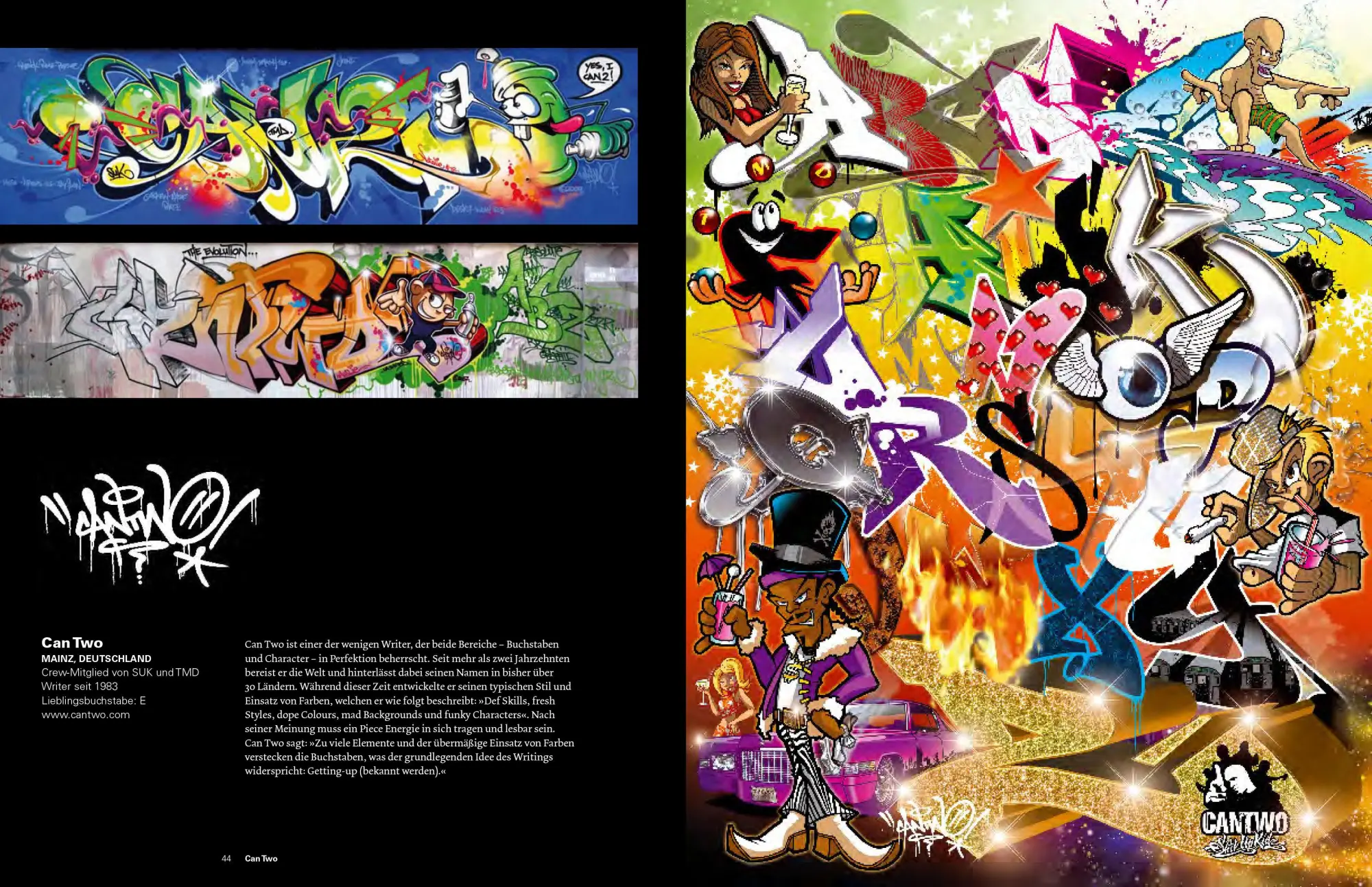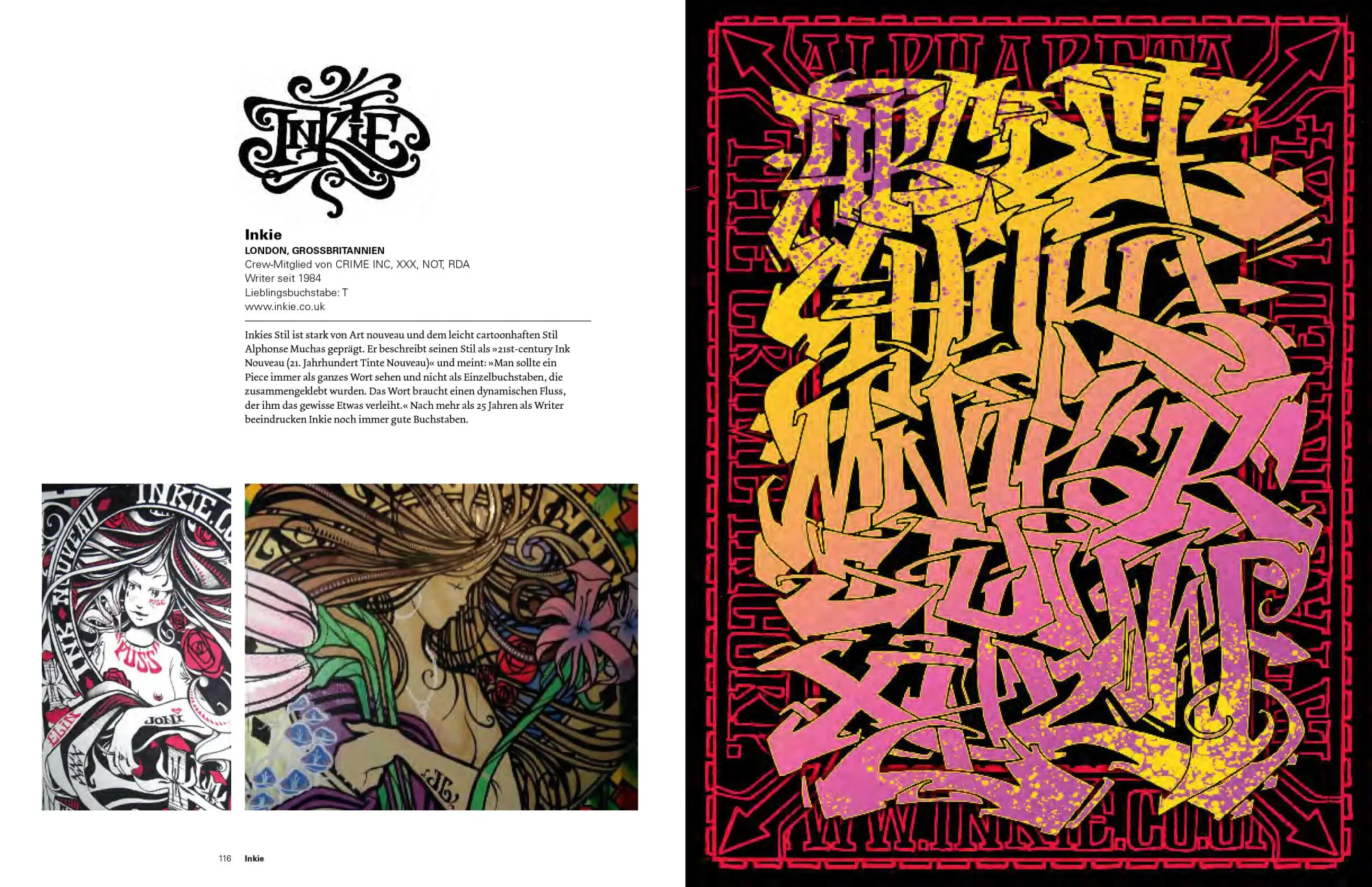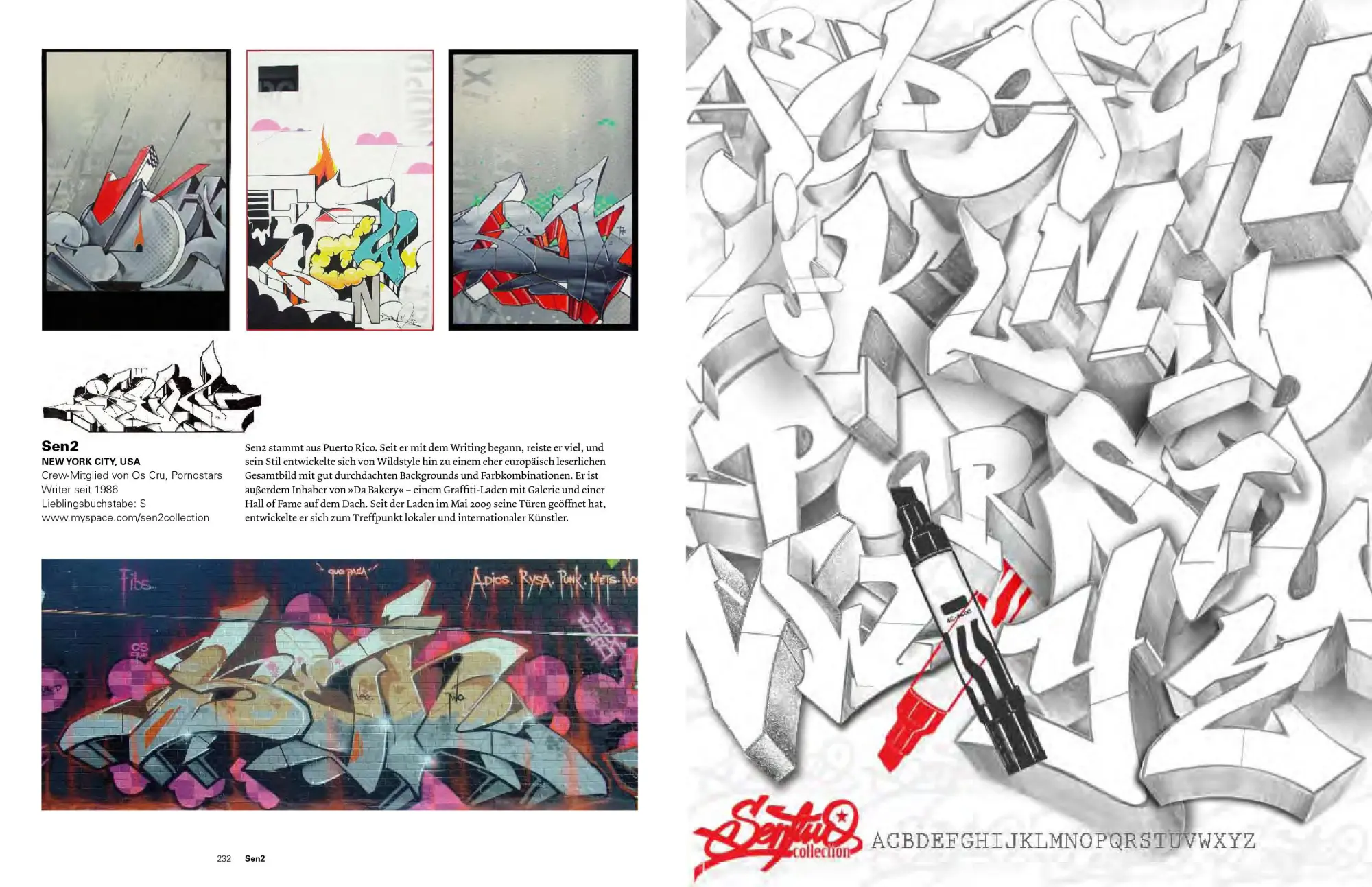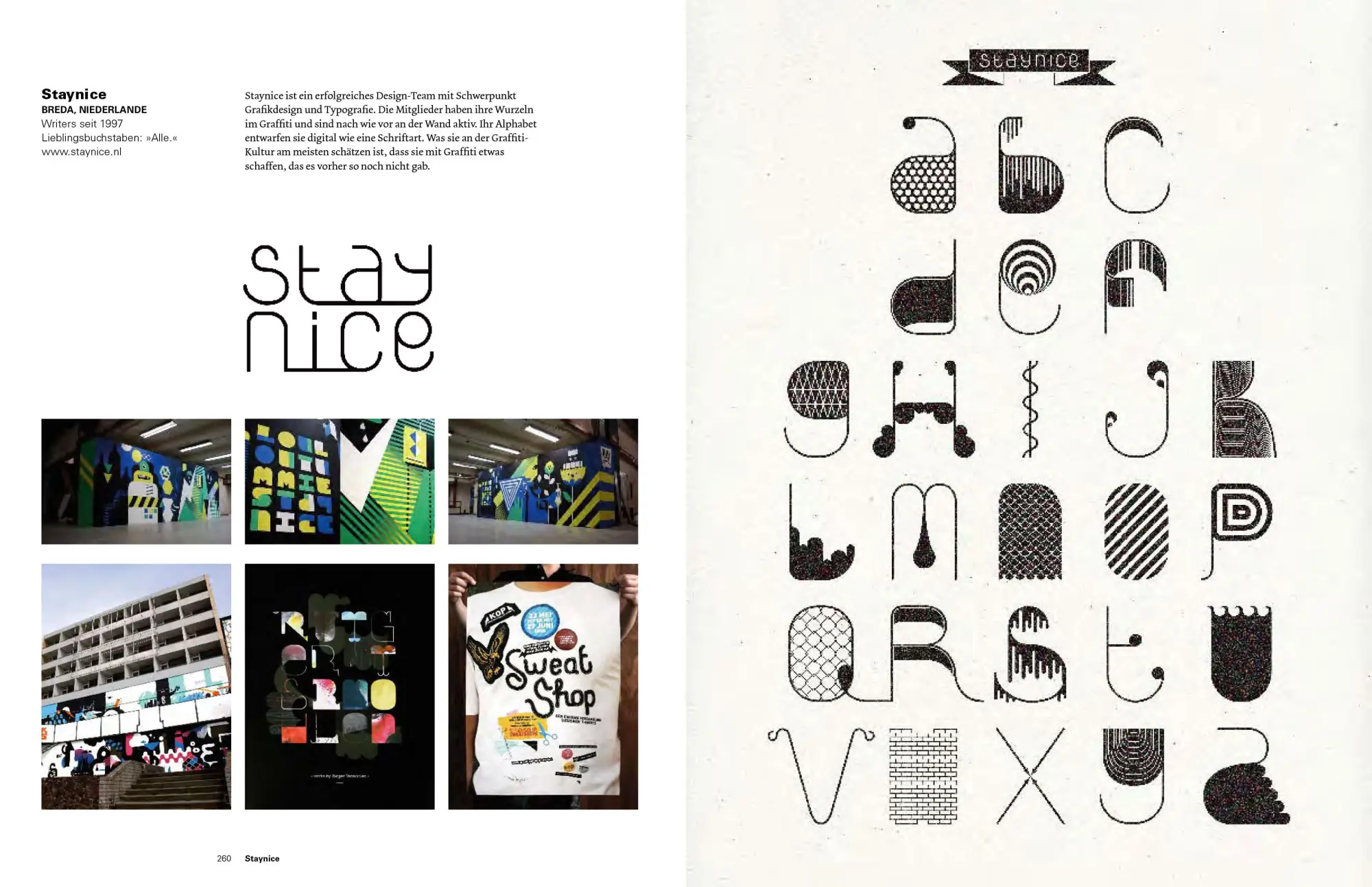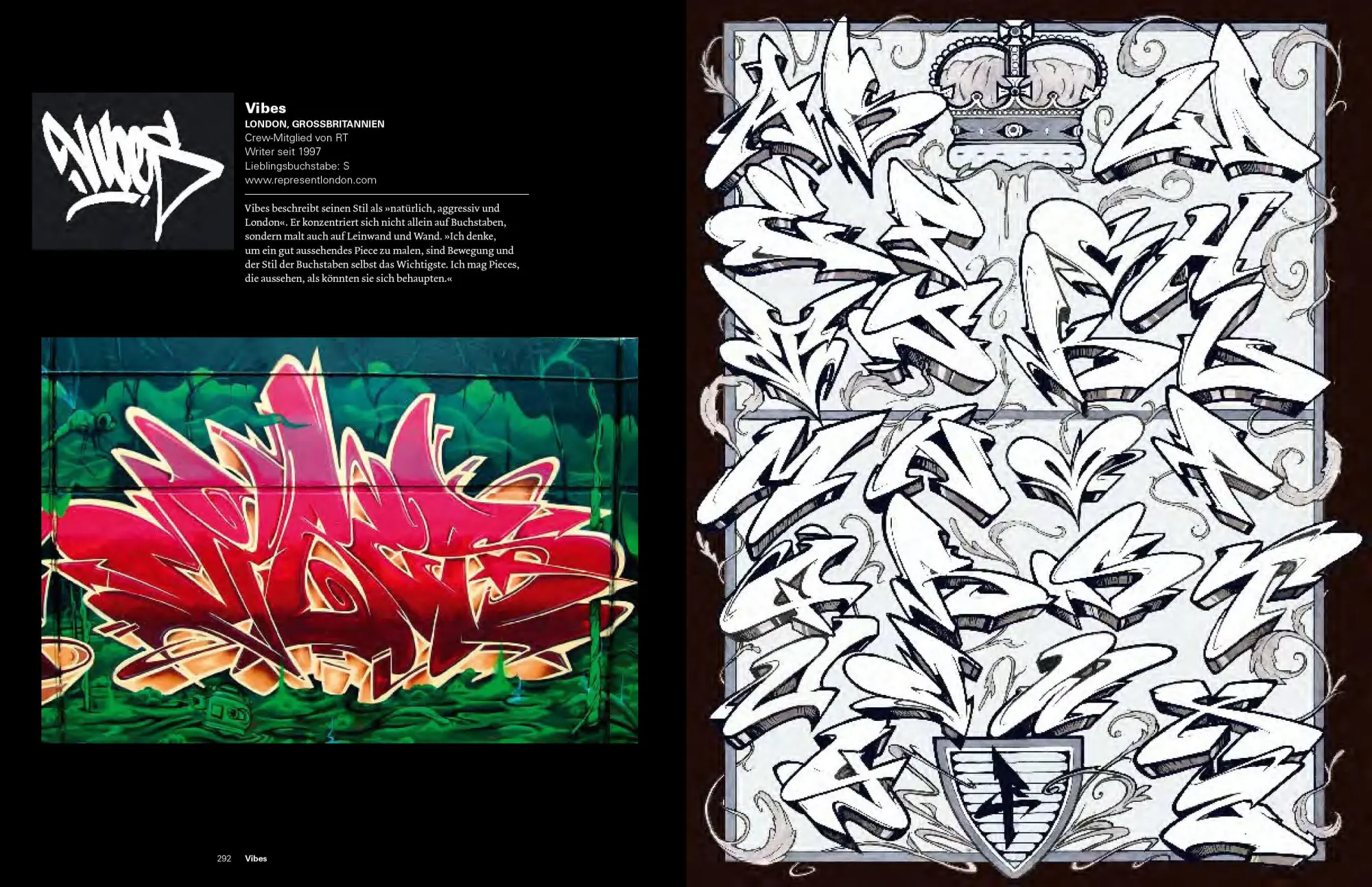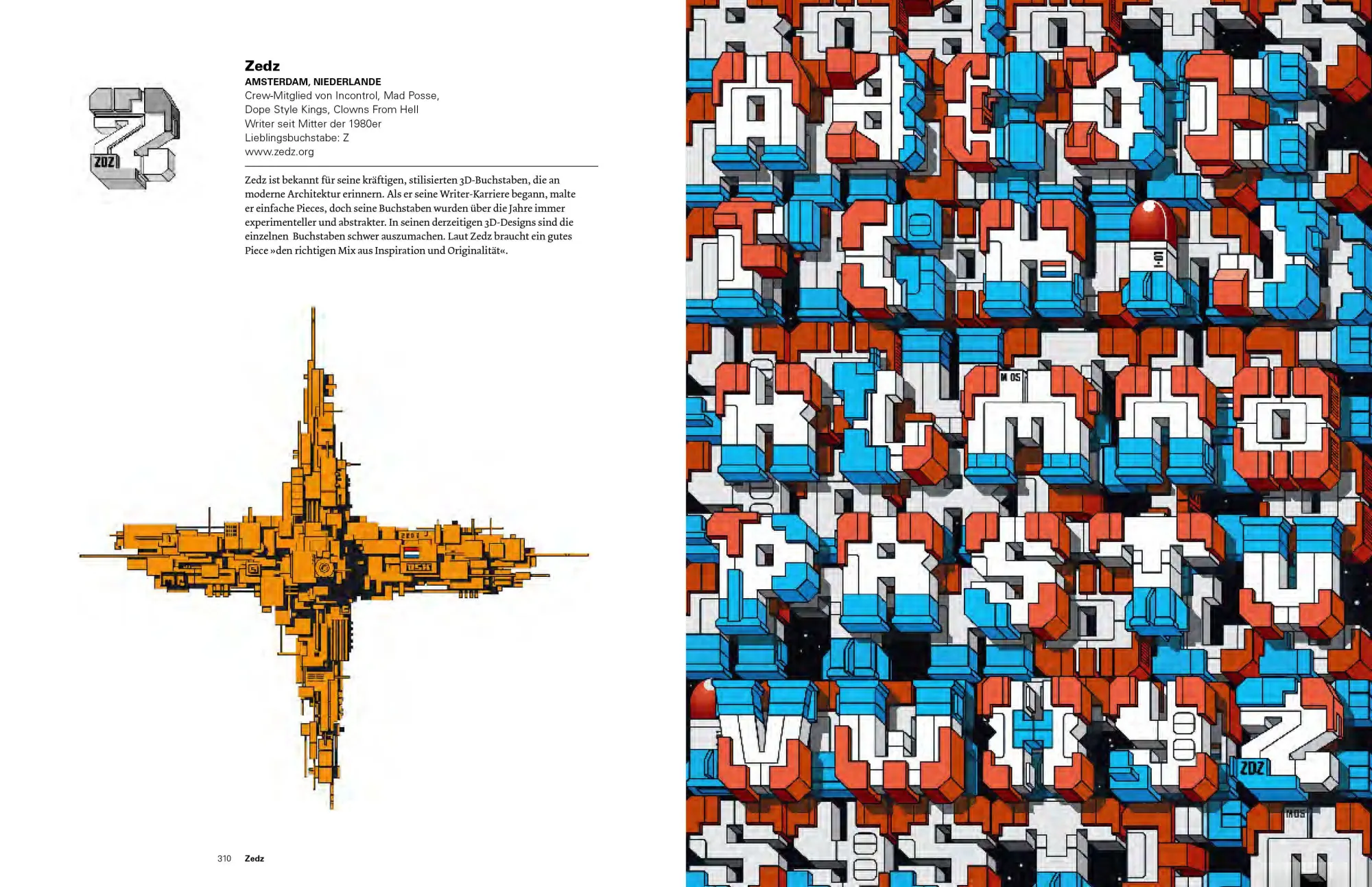
Das Alphabet der Straße
Dieser Band ist die perfekte Inspirationsquelle für Designer, Grafiker, Gestalter, Typografen und alle, die sich für Street Art interessieren. Mit mehr als 150 eigens für diesen Band entworfene Schriften von internationalen Graffiti-Artists, darunter auch die wichtigsten deutschen Künstler, u. a. aus Berlin, Dortmund, Dresden, Frankfurt, Hamburg, Köln, München, Stuttgart.
Graffitis begleiten vor allem Großstädter in aller Welt auf dem Weg durch ihre Stadt. Hier hat sich in den letzten Jahren eine ernst zu nehmende Szene etabliert, die längst den Weg von der Straße bis in renommierte Galerien gefunden hat. Viele der Straßenkünstler haben sich mit einer eigenständigen Schrift als Markenzeichen einen Namen gemacht. Dieser Band stellt über 150 Graffiti-Schriften zusammen, die Street-Artists aus der ganzen Welt für dieses Buch entworfen haben. In grafischem Schwarz-Weiß oder bunt und farbenfroh, figural oder quasi abstrakt, in skulpturalen Formen, fetten Lettern oder filigranen Linien repräsentieren diese Alphabete die internationale Street-Art-Szene und geben Einblick in den faszinierenden Kreativprozess des Graffiti-Writing. Ideal und unentbehrlich als Inspiration und Vorlage für Street-Artists und alle, die sich für Graffiti, Design und Typografie interessieren.
Claudia Walde, alias MadC, zählt zu den weltweit bekanntesten Graffiti-Künstlerinnen, ihre Arbeiten waren bereits in über 35 Ländern zu sehen. Im Prestel Verlag erschienen ihre Bücher Street Fonts - Graffiti-Schriften von Berlin bis New York und Graffiti XXL: Street Art im Großformat.
Viele deutsche Graffiti-Künstler aus Berlin, Bremen, Dortmund, Dresden, Frankfurt, Halle, Hamburg, Heidelberg, Koblenz, Köln, Mainz, München, Stuttgart, Wiesbaden
Aus der Schweiz: Basel, Bern, Zürich